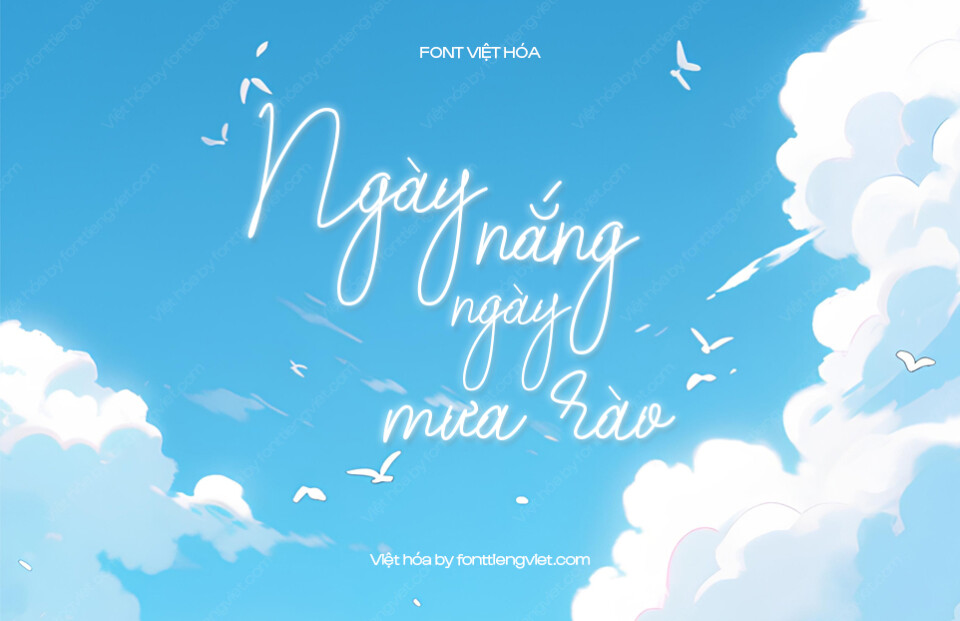
Giới thiệu về Font Việt hóa 1FTV VIP Brotherside Signature
Trong thế giới đồ họa hiện đại, việc tìm kiếm một bộ Font Chữ mang phong cách viết tay thanh lịch là điều vô cùng quan trọng. Font Việt hóa 1FTV VIP Brotherside Signature chính là sự lựa chọn hoàn hảo cho những ai yêu thích sự mềm mại và cá tính. Đây là một bộ phông chữ ký (signature) được chăm chút kỹ lưỡng về đường nét, tạo cảm giác tự nhiên như nét bút thật trên giấy. Với phiên bản Việt hóa chỉn chu, người dùng có thể dễ dàng sử dụng các ký tự tiếng Việt có dấu mà không lo bị lỗi hiển thị, giúp quy trình thiết kế trở nên mượt mà và chuyên nghiệp hơn rất nhiều.
Đặc điểm nổi bật của bộ font chữ ký này
Phong cách thiết kế sang trọng
Font Việt hóa 1FTV VIP Brotherside Signature nổi bật với những đường nối chữ bay bổng, tạo nên một tổng thể hài hòa và đầy tính nghệ thuật. Bộ font này rất phù hợp cho các bài tập thiết kế thiệp mời, bìa sách giáo khoa hoặc các ấn phẩm truyền thông trong nhà trường. Sự tinh tế trong từng nét thanh nét đậm giúp thông điệp truyền tải trở nên gần gũi và giàu cảm xúc hơn.
Tính ứng dụng thực tế cao